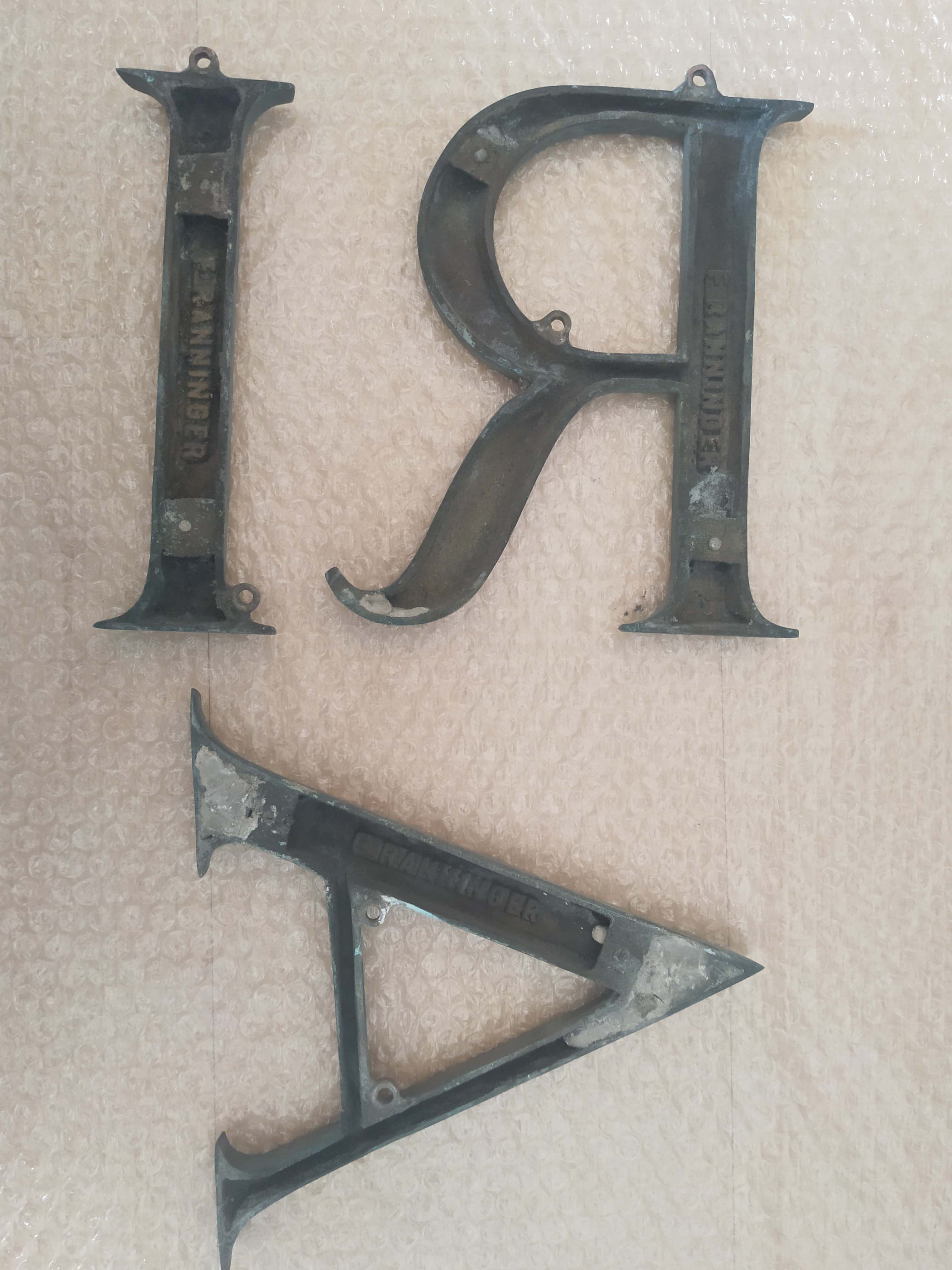
¿Cuánto costaba hacer un rótulo en los años 40?
¿Os acordáis de cuando se salvaron las letras de la «Joyería Salamanca»? Pues hay nueva información. Recientemente, gracias a la familia, ha aparecido la Factura original del encargo. Ahora sabemos cuánto costaron y quien las realizó. El coste de las 25 letras fue de 1.425 pts de 1948, que junto con otros rótulos para el mostrador y portes, el total fue de 1.652 pts (pensad que unn profesor andaría ganando sobre 1000 pts)
Las letras al verlas por su reverso estaban firmadas por «F. Ranninger». «Fernando Ranninger» era un taller de Madrid, referente en esta industria de la rotulación. Ya en 1933 aparecía un anuncio suyo en una revista «Actividad Contemporánea«, dedicada a Arquitectura, Ingeniería y Diseño Industrial.
Otra curiosidad de la revista. Aparece un anuncio de Jacobo Schneider SA, que realizó el Cuadro de Maniobra del antiguo Hospital Universitario Marqués de Valdecilla. Schneider os sonará de los ascensores ¿no? Ranninger, también aparece como uno de los proveedores de las obras temporales del Museo de América en Madrid, en el año 44, con el encargo de las Letras. En ese listado sale otro nombre: Pereantón. ¿quién es Perenatón? Muy fácil. Hablamos de ellos hace poco, cuando lanzamos la campaña desde la @patrimografico de salvar el rótulo de «Curtidos Baranda» (https://www.facebook.com/patrimoniografico/posts/158503569047668)